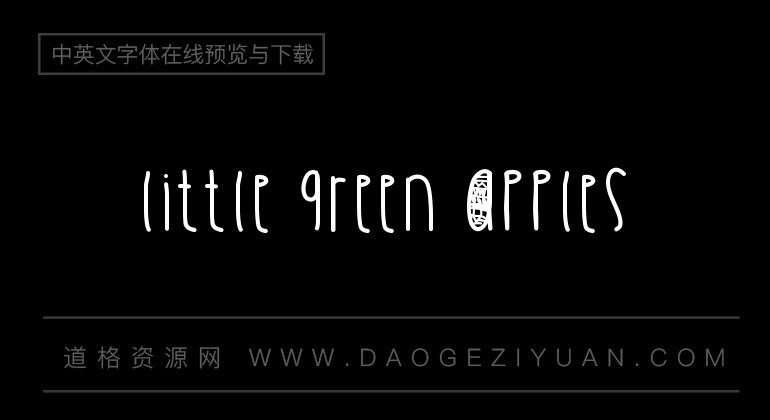
Little Green Apples
Little Green Apples 是一款清新可爱的字体,由英国设计师Gemma O’Brien设计,可用于商业和个人项目。Little Green Apples字体具有明朗的外观,拥有完整的字母、数字和符号,以及支持多种语言。它可以用于各种文档,包括海报、网站、商业广告和书籍等。Little Green Apples字体特别适合用于创造温馨、可爱的设计,可以带给人们温暖的感觉。
Little Green Apples是一款非常不错的手写艺术字体,具有很好的视觉感,适合于文化类的宣传设计、商业类品牌的广告和产品包装设计以及个性化文字排版等较多场景。